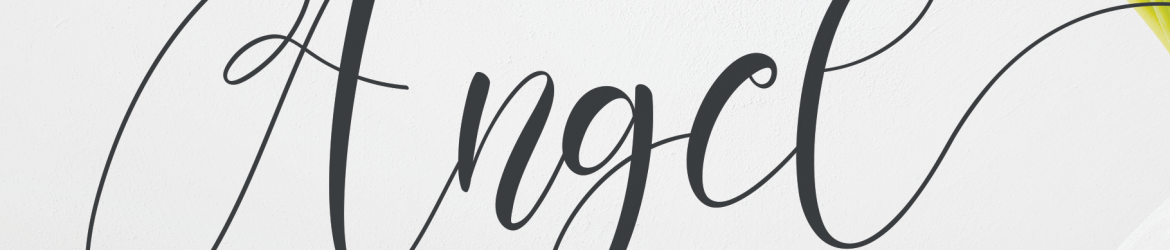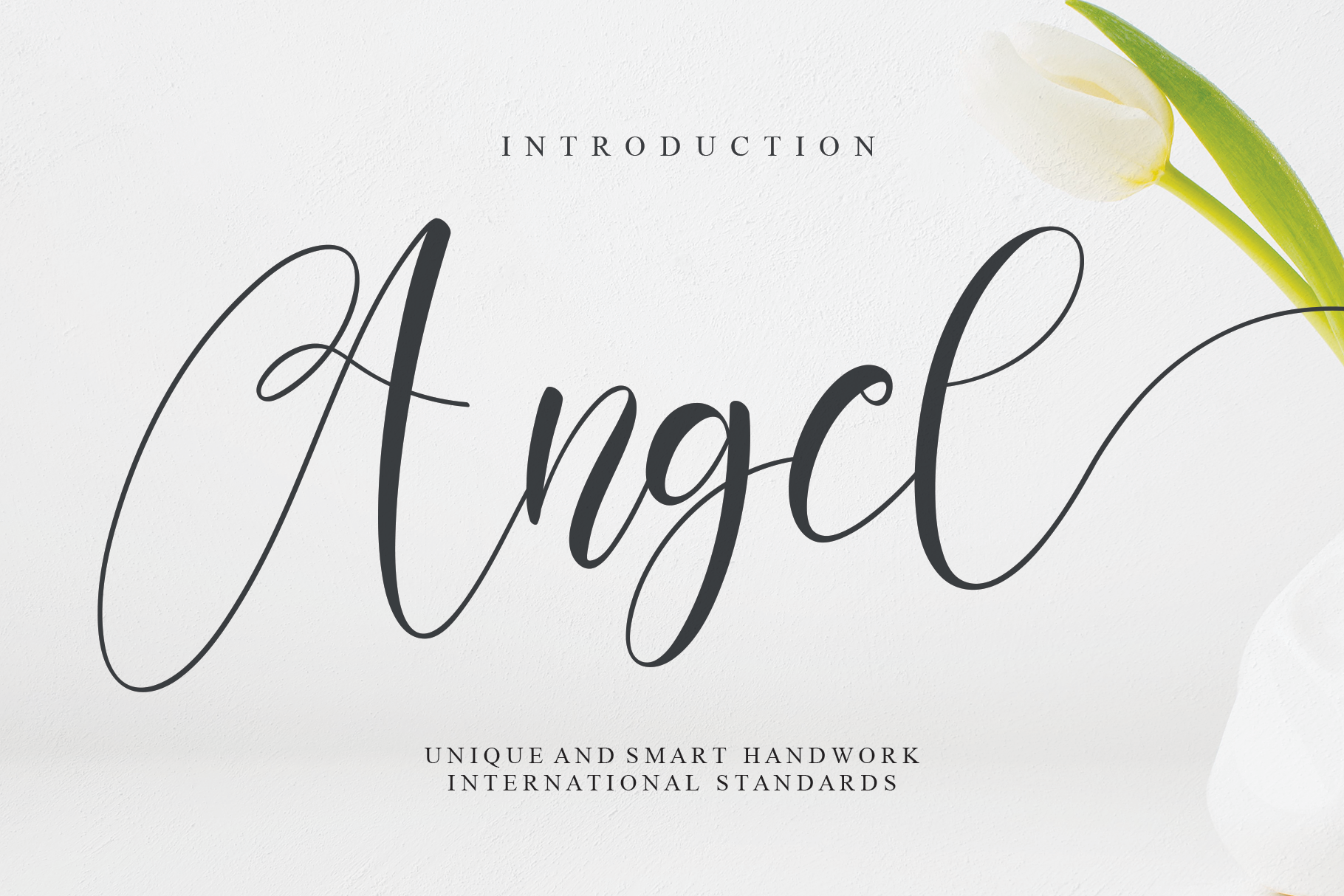
Angel Font
A fonte ‘Angel Font’ é uma elegante tipografia script que oferece um estilo refinado e delicado. Com sua aparência limpa, fina e macia, ela adicionará um toque singular a qualquer projeto design que você adicione. Ideal para elementos de texto pessoais, desenhos gráficos ou qualquer arte em que deseje criar um toque sofisticado e suave. Este é o tipo certo se você procura uma fonte para dar um toque único à sua próxima criação visual, seja ela digital ou impressa. Aprenda mais sobre como a ‘Angel Font’ pode ajudar a transformar seus projetos em algo realmente especial.